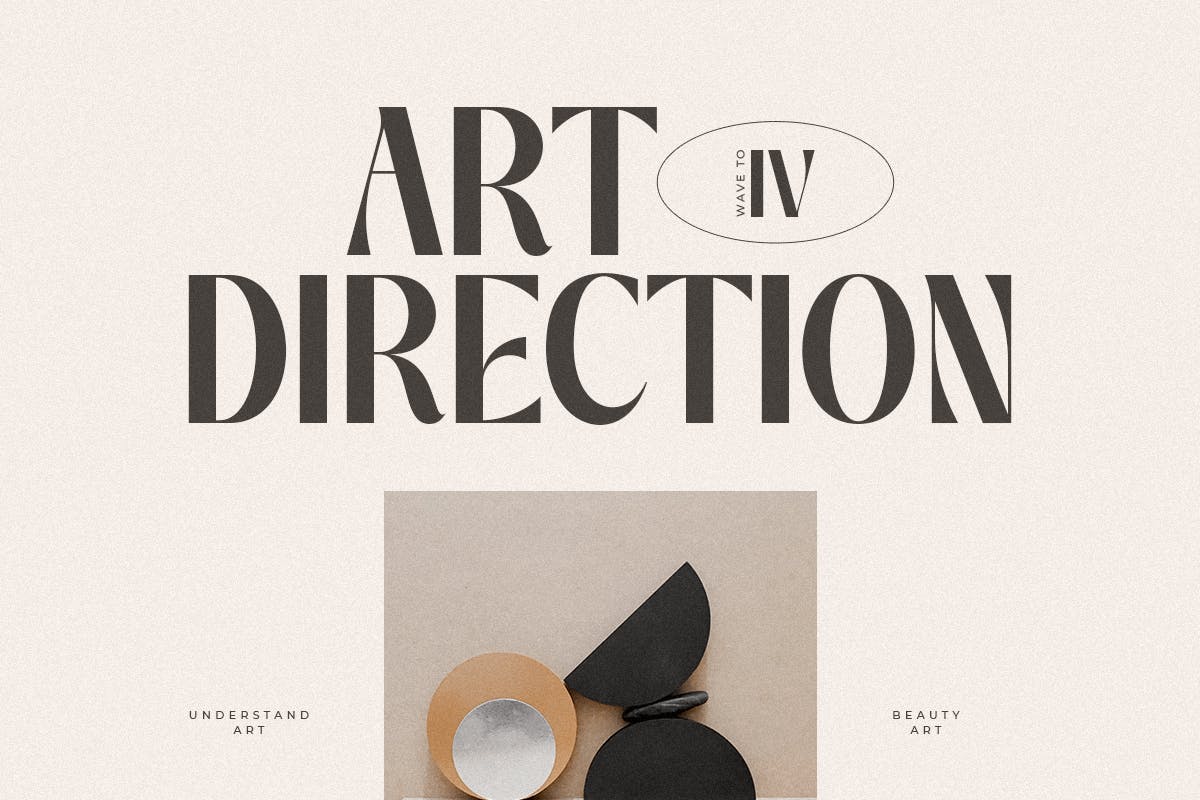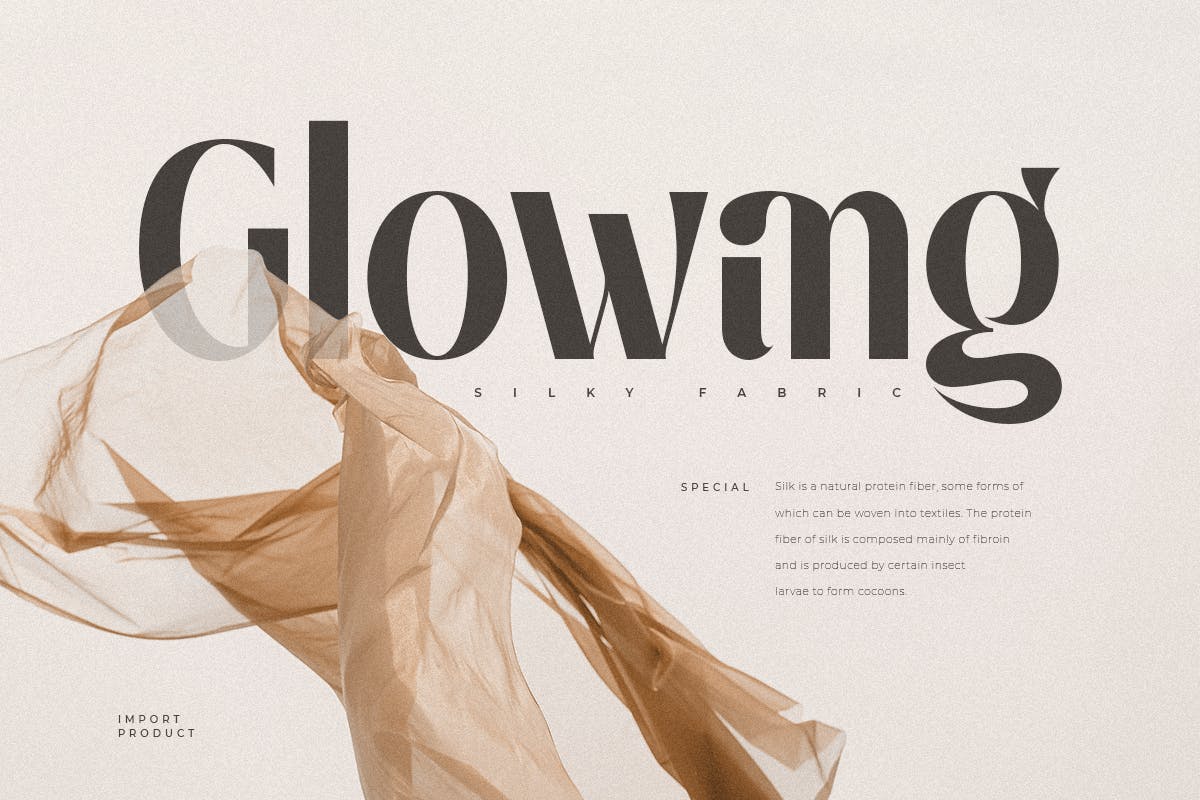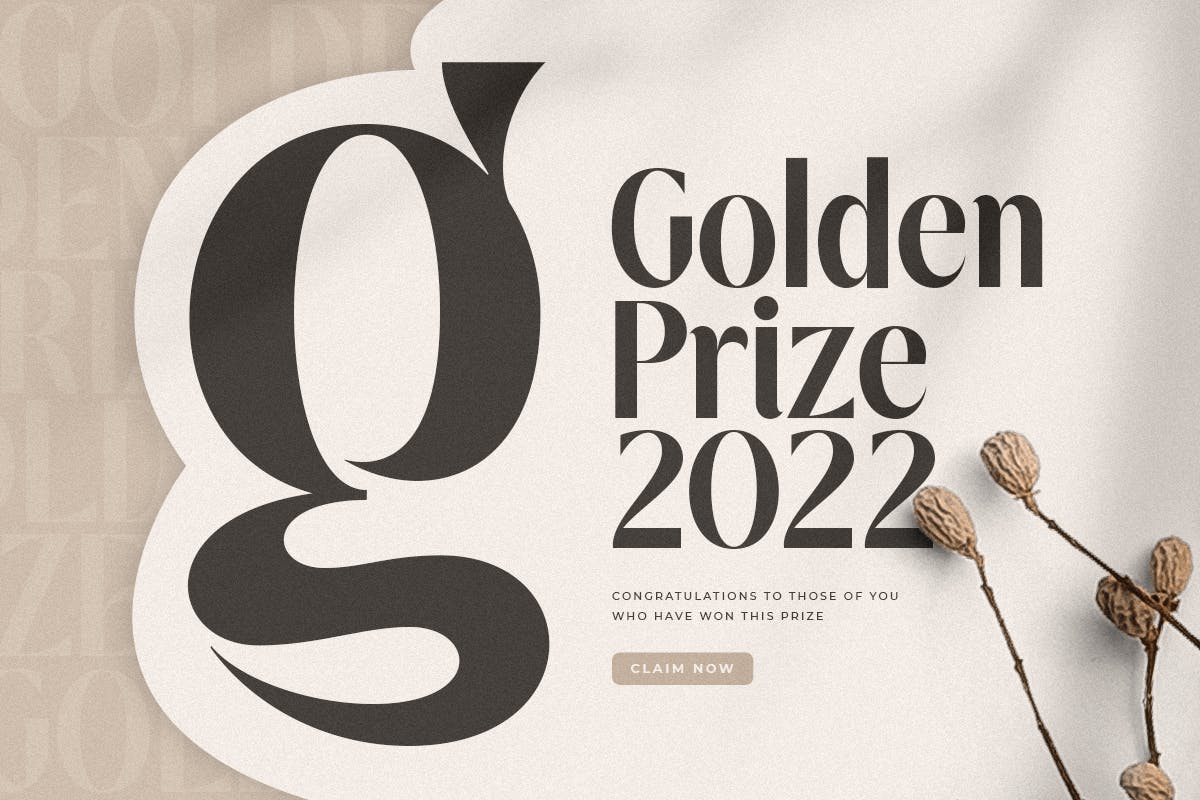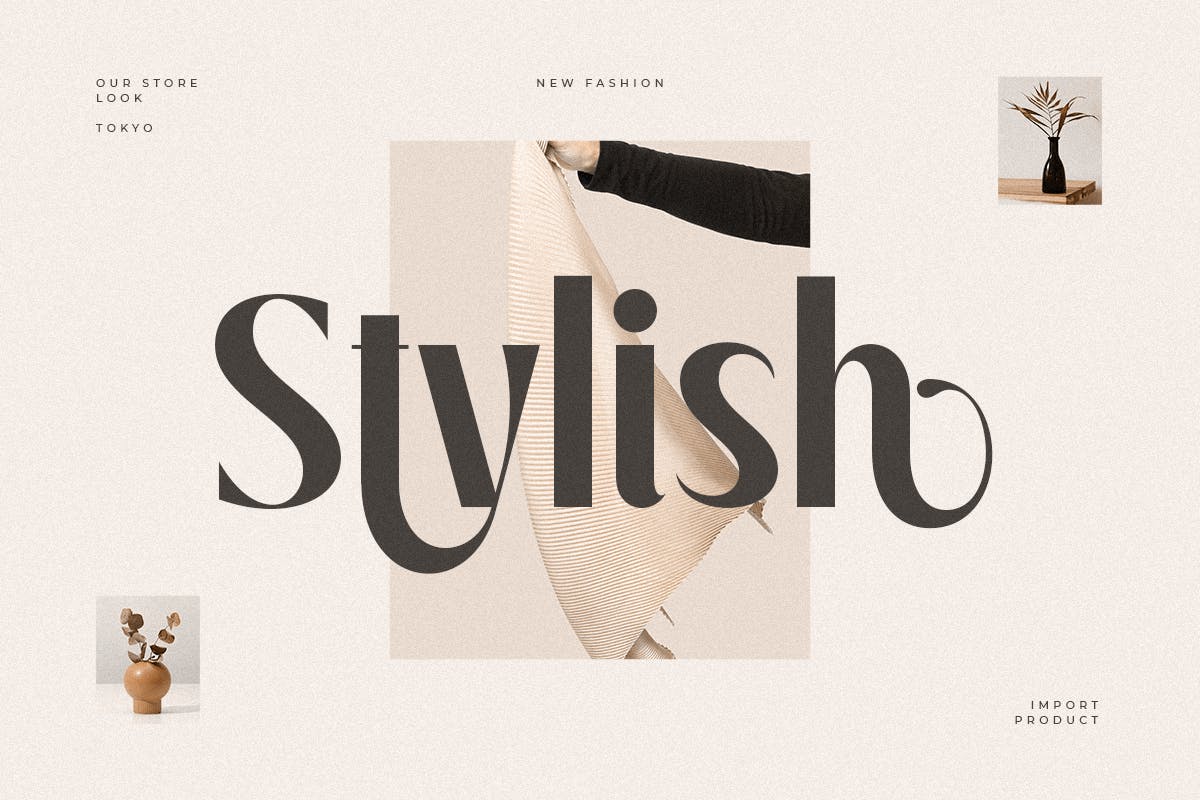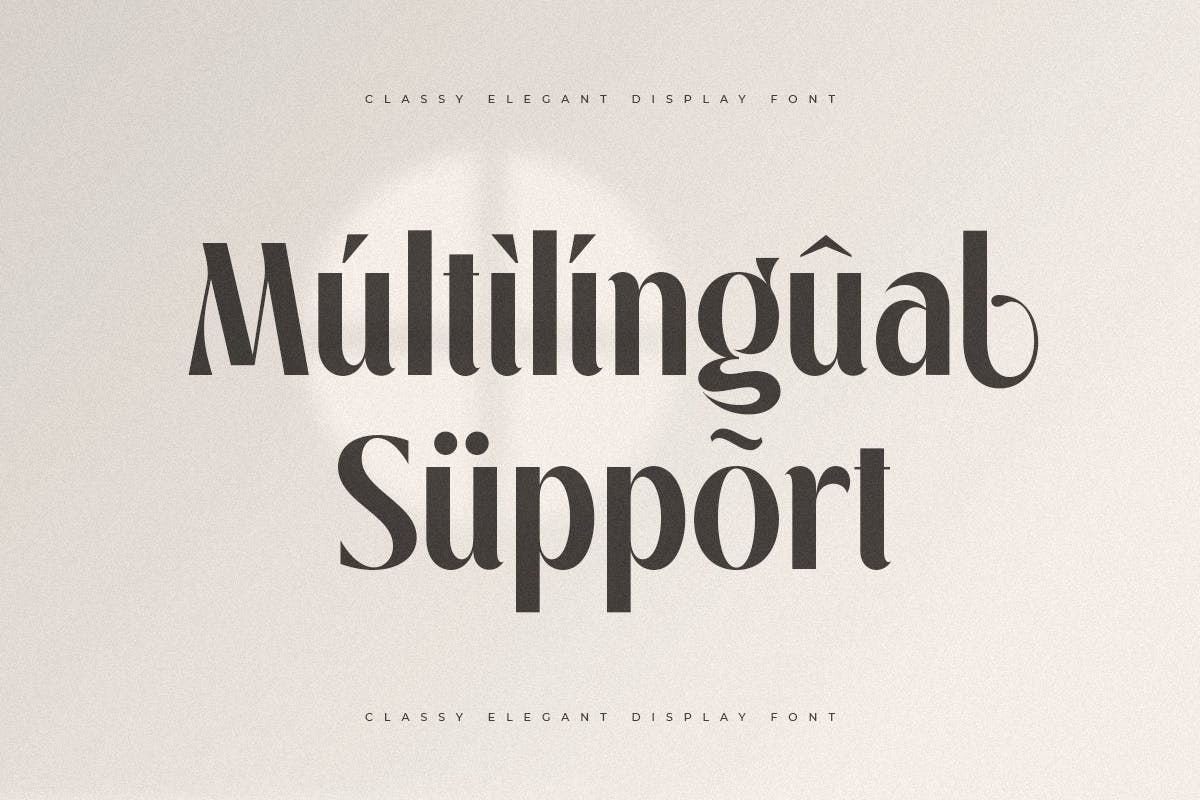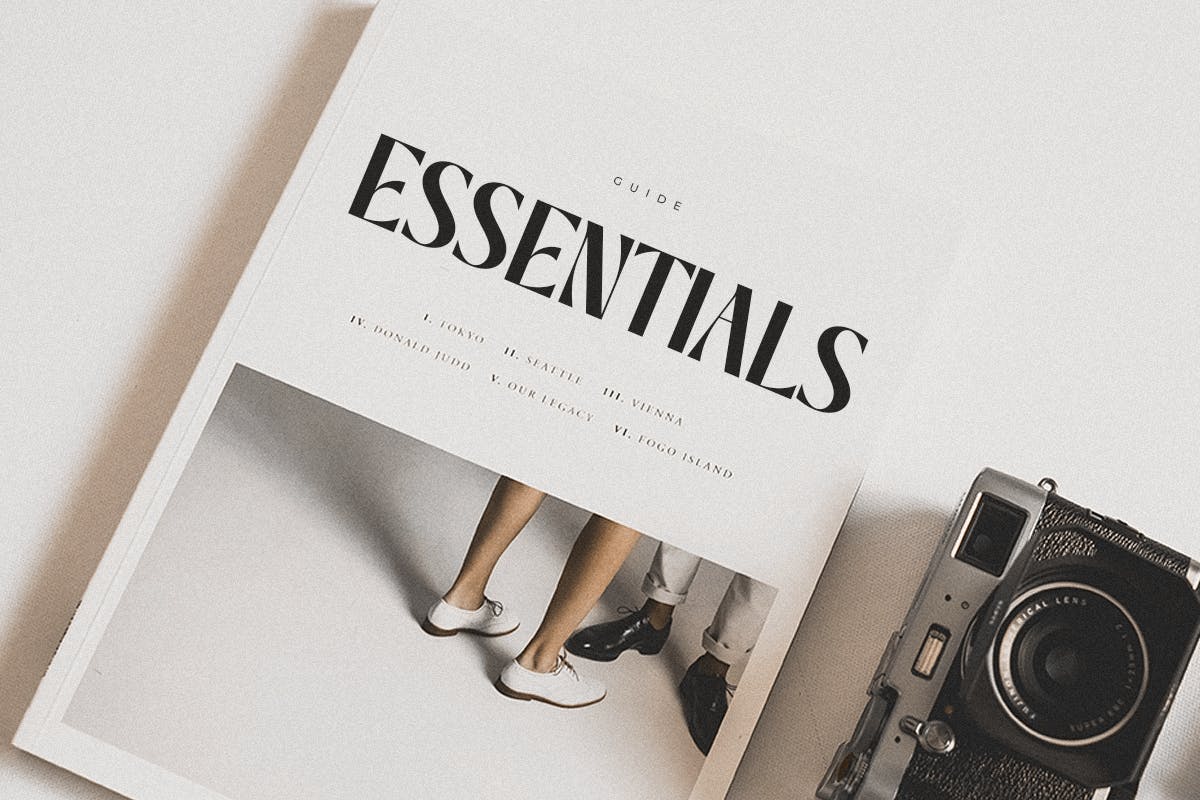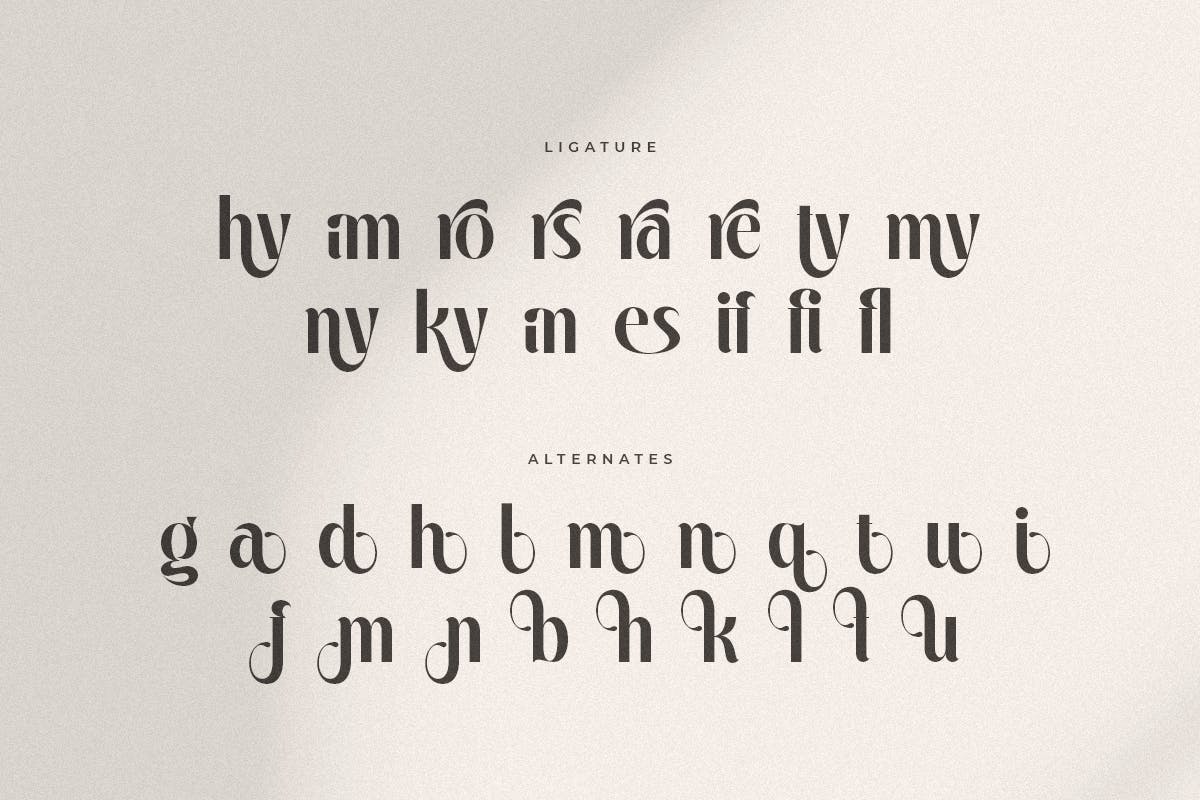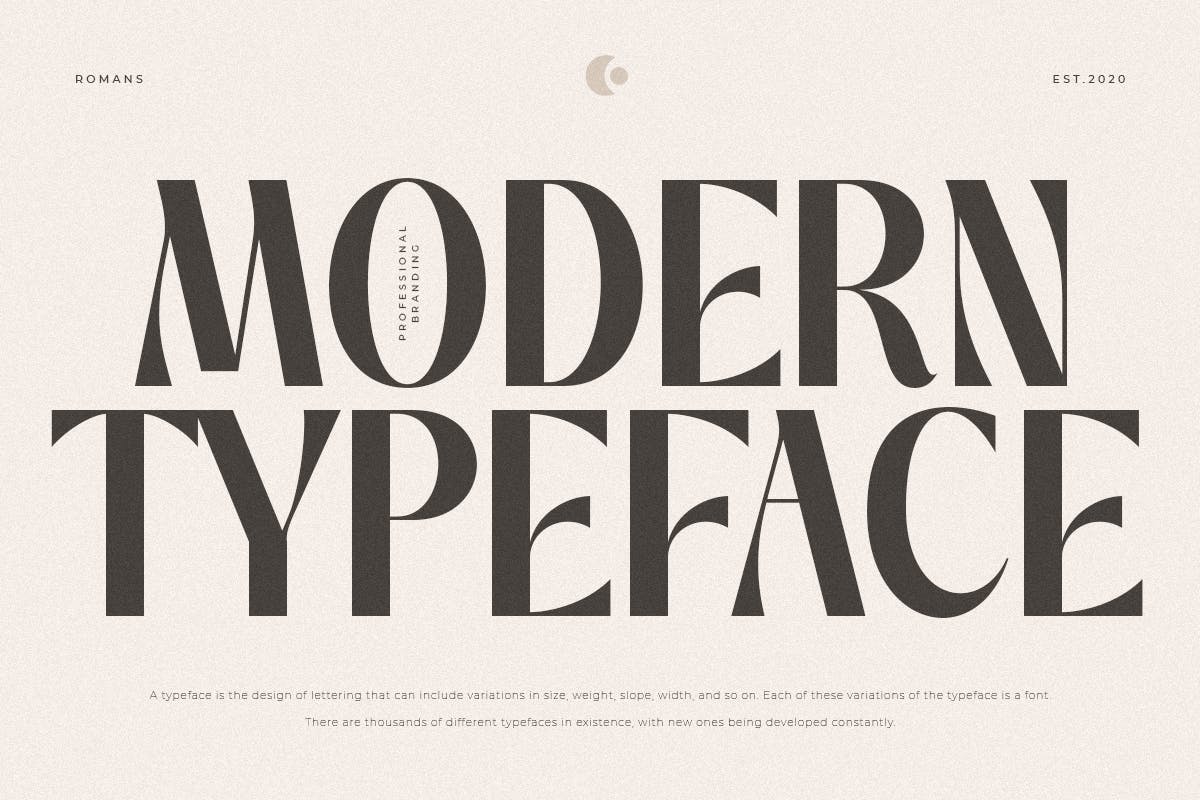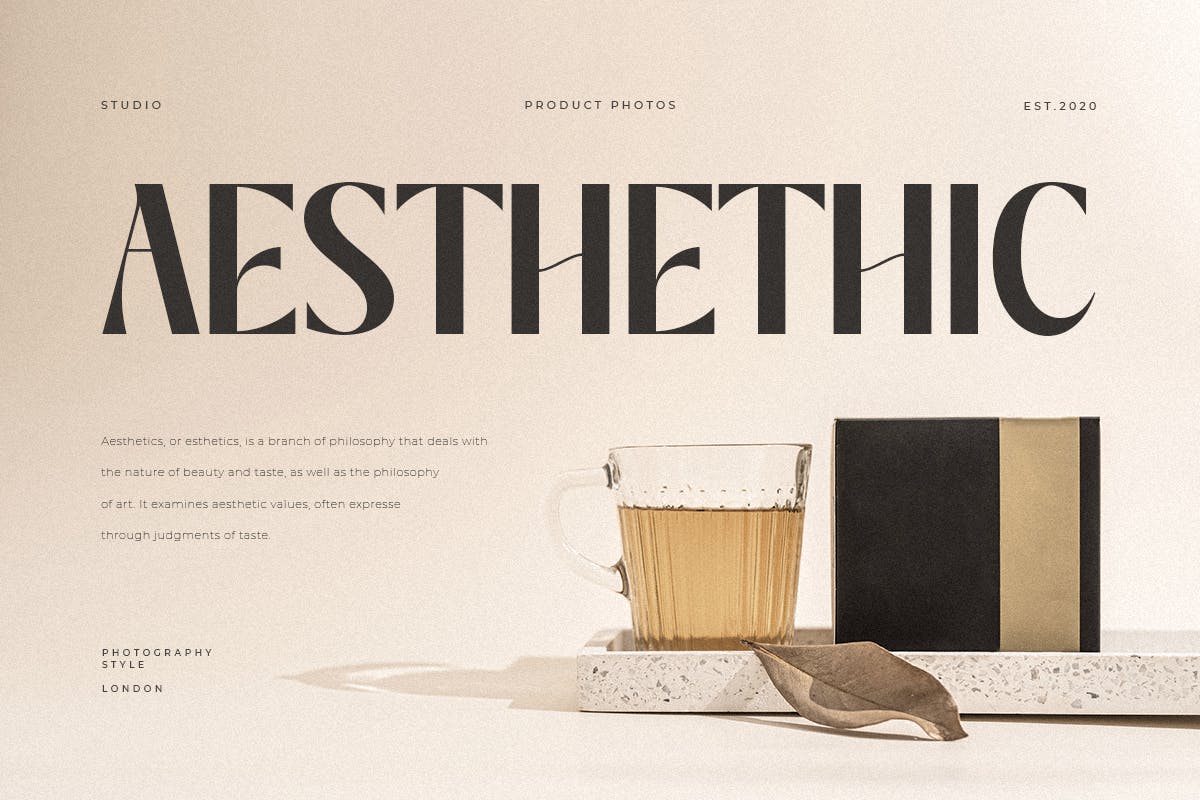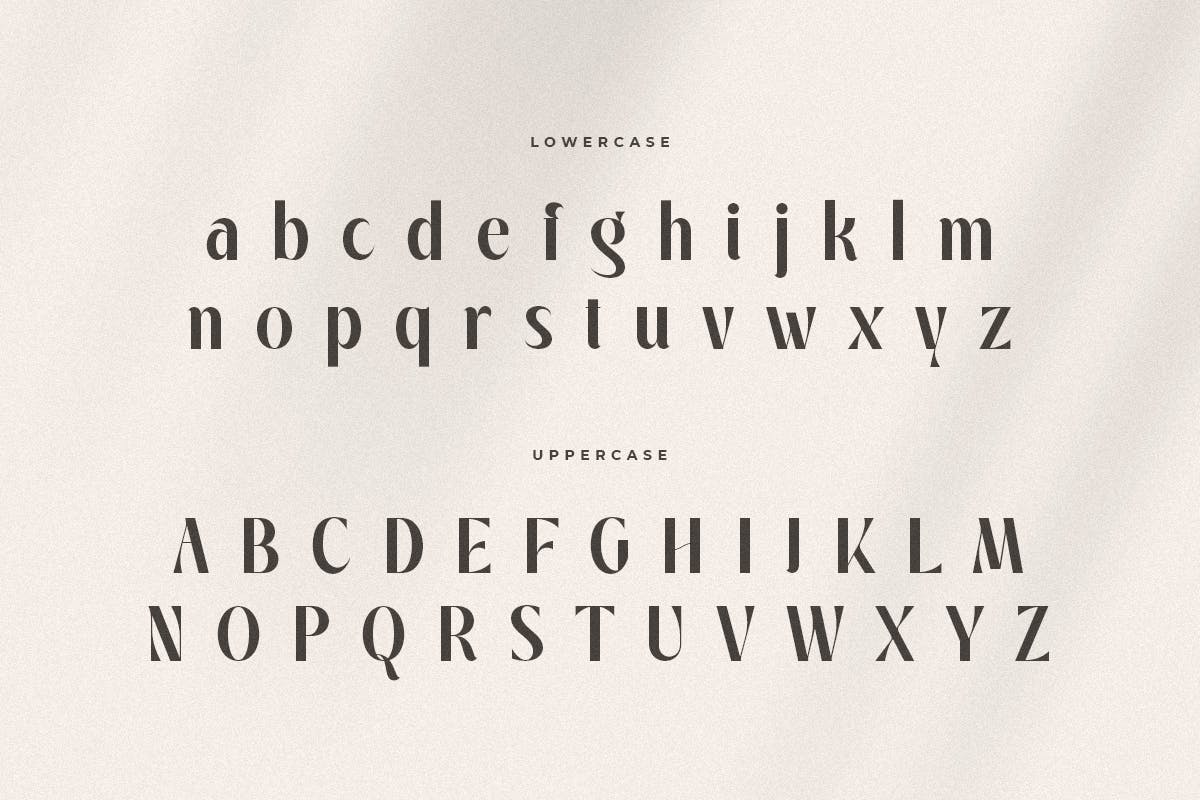
فونت Manyfit Classy Elegant Luxury یک فونت لوکس و کلاسیک است که به ویژه برای نیازهای برندینگ شیک طراحی شده است. با شکل منحصر به فرد خود، این فونت ارزش افزودهای به برند شما اضافه خواهد کرد. این فونت به طراحان و صاحبان محصولات کمک میکند تا طراحیهای خود را مدرن و شیکتر جلوه دهند. ما برای فونت Manyfit، مجموعهای از کاراکترها را آماده کردهایم تا به شما در ایجاد تغییرات نامحدود برای نیازهای خلاقانهتان کمک کنیم.